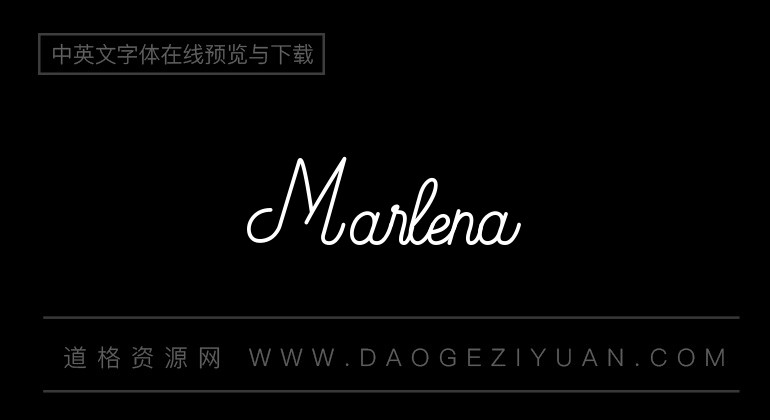
Marlena
? Marlena 字体是一款细腻的草书字体,它具有精致的线条和柔和的曲线,使其看起来更加优雅,更易于阅读。它的字形更加自然,易于扩展,可以更好地适应不同的尺寸和环境。Marlena 字体适用于印刷品、网站、应用程序以及其他任何地方,可以提供清晰、美观的文本,令您的设计更加优雅和精致。
Marlena是一款非常不错的手写艺术字体,具有很好的视觉感,适合于文化类的宣传设计、商业类品牌的广告和产品包装设计以及个性化文字排版等较多场景。
Marlena字符映射图